楷书字体一般都是很工整、规范的,书写出来的效果也是很好的,所以也就深受广大朋友们的喜欢;今天和大家分享的是义启字库中适用于当做字帖的两款楷书字体,欢迎有需要的朋友到字体视界下载。
1、义启粗楷体
义启粗楷体大量吸取了唐楷的元素,不但笔画上浑厚有力,机构上也收放夸而不张。整个字变的生动活泼起来,而字与字之间也遥相呼应,整体读来一气呵成。无论线条、结构还是章法都使得粗楷独树一帜。
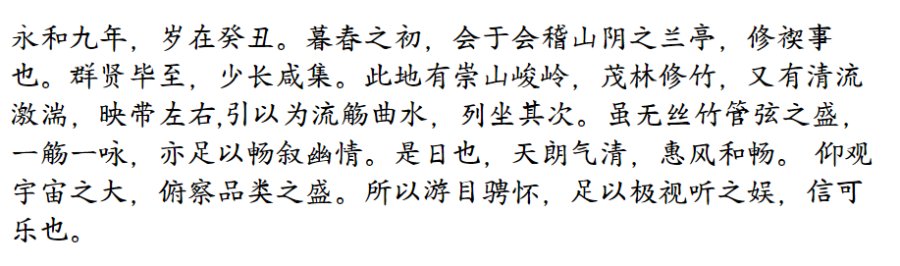
2、从此天涯是路人
从此天涯是路人是一款不错的艺术字体,由义启字库出品字体笔触粗细适中,书写端正,具有很好的视觉感,适合应用于艺术设计、平面宣传设计、网页设计,书法字帖等领域。